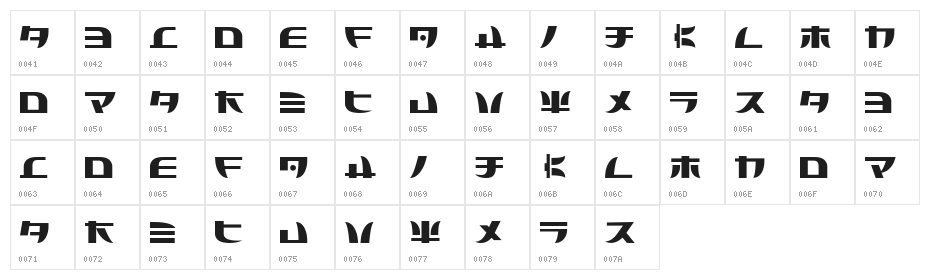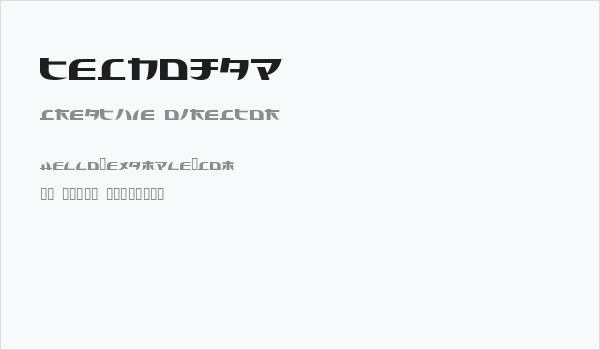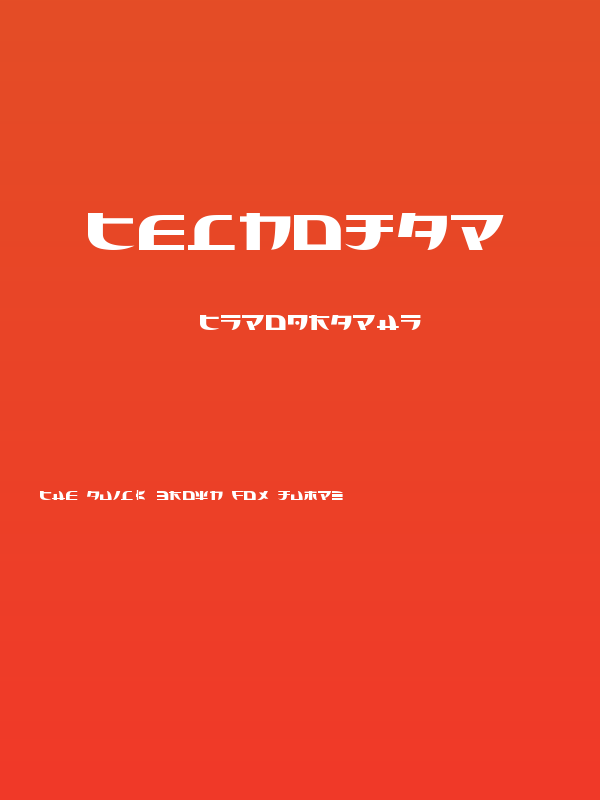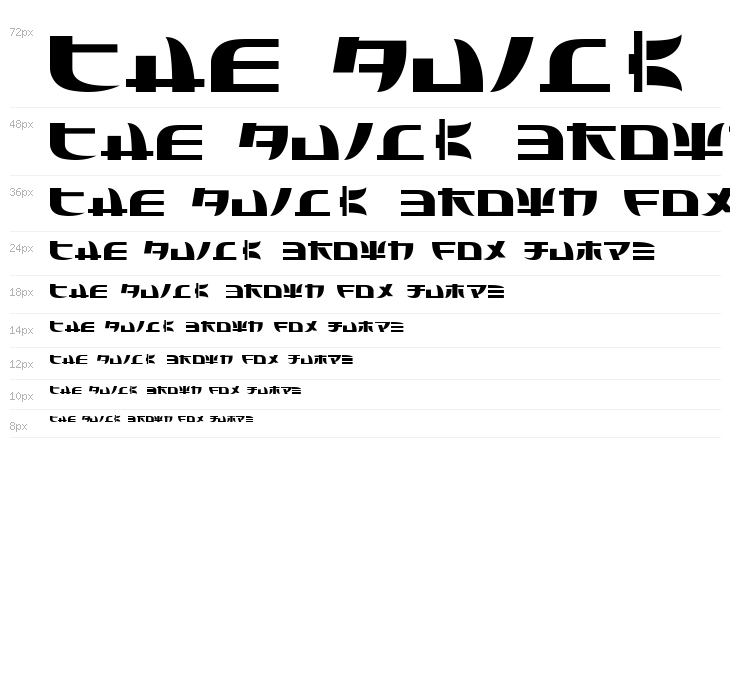
Tecnojap Font
| Categorie | Capitals |
| Caso d'uso | Logos, Headlines |
| Progetti proposti | Ideal for technology branding, sci-fi movie posters, video game titles, and digital media. |